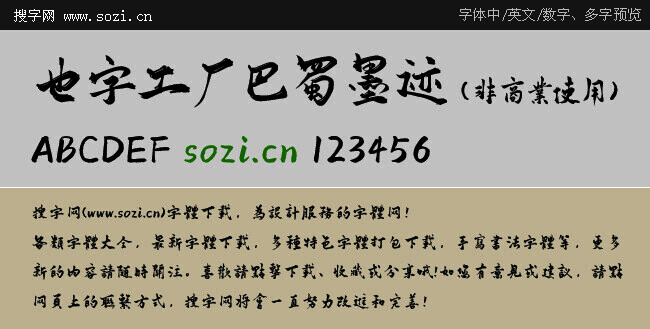
也字工廠巴蜀墨跡
搜字網給大家提供一款也字工廠巴蜀墨跡(非商業使用)中文字體下載,也字工廠巴蜀墨跡是一款書法字體,全套字體采用繁體進行設計,最大程度保留了字體中筆墨書寫的痕跡,還原了書法字體該有的本真質感。適合應用于海報設計、包裝設計、網頁設計等應用(此字體為個人非商用版,商用可以聯系:官方網址:https://yefont.com/home,聯系方式:13798980448)。